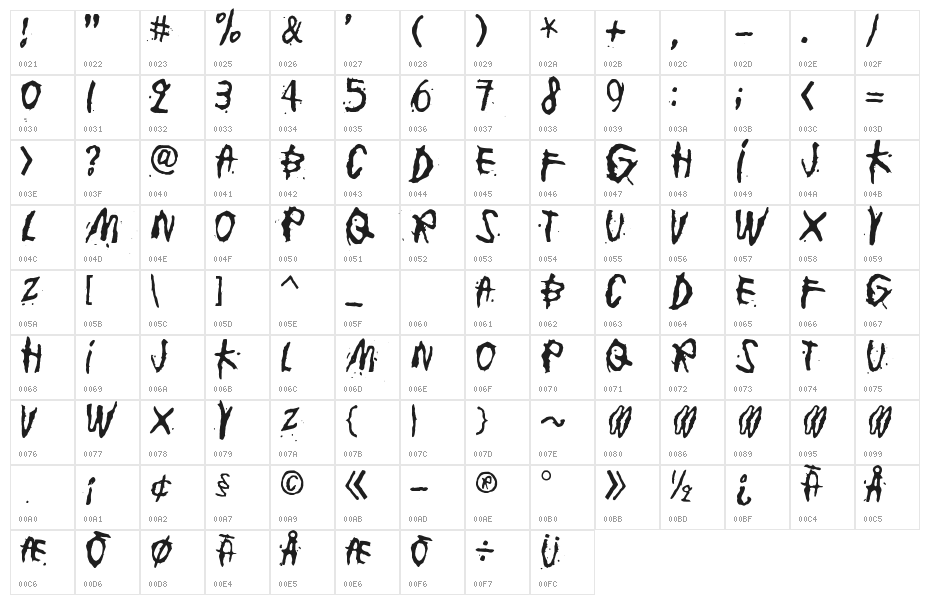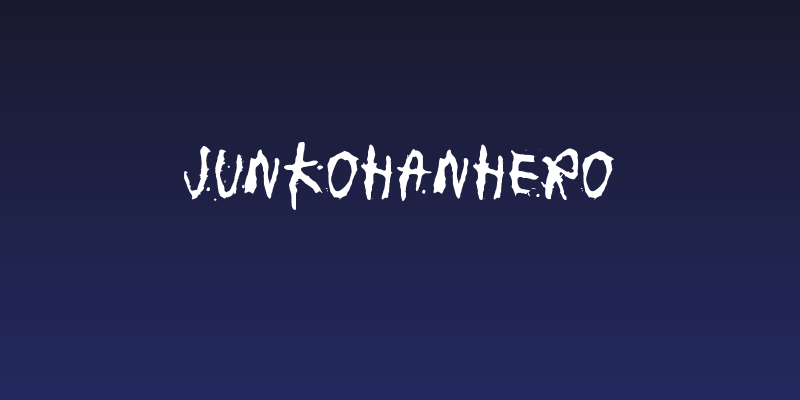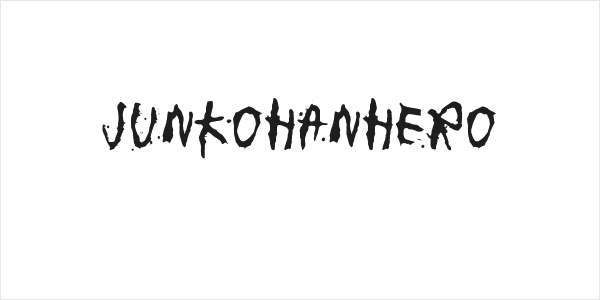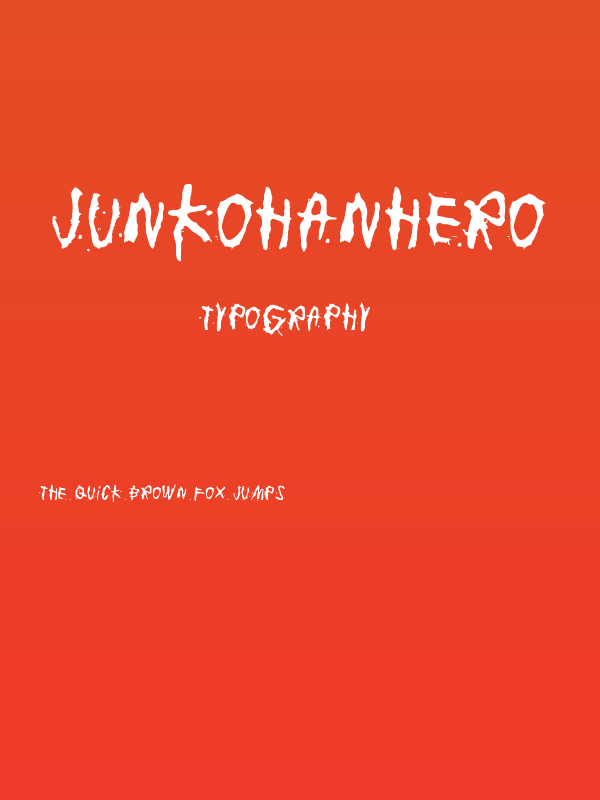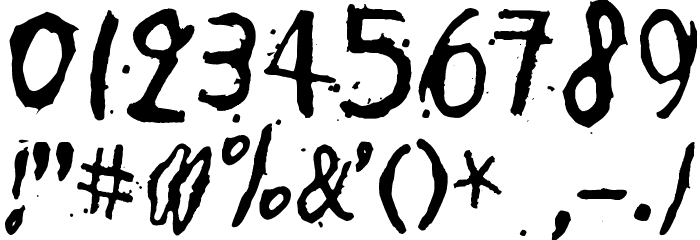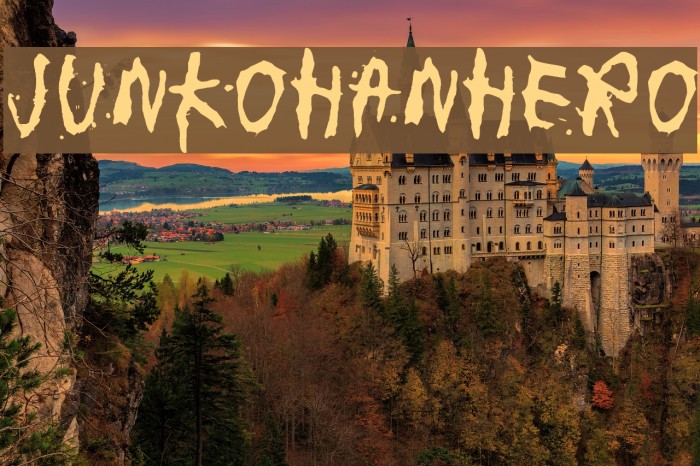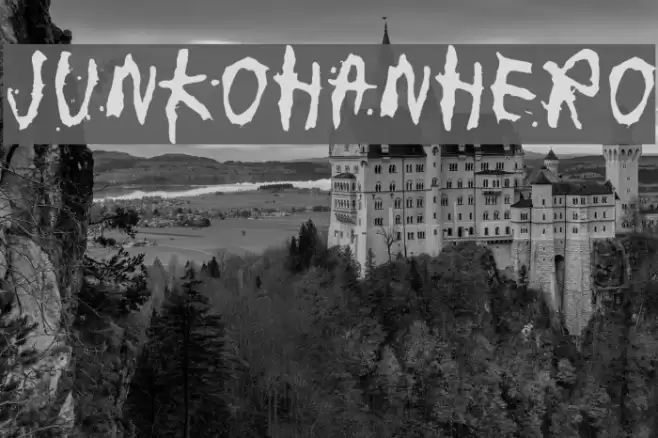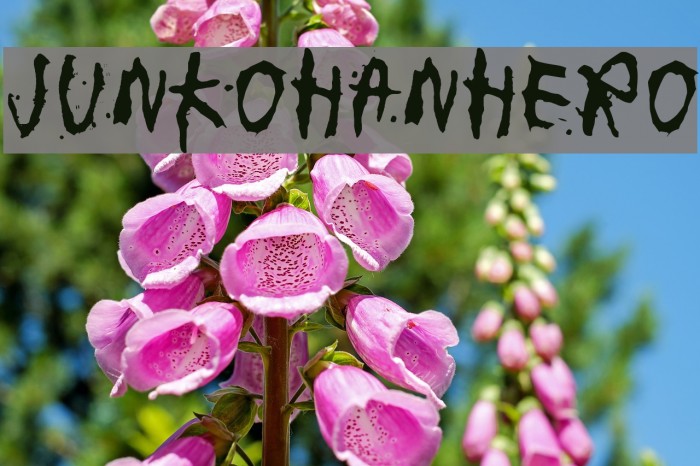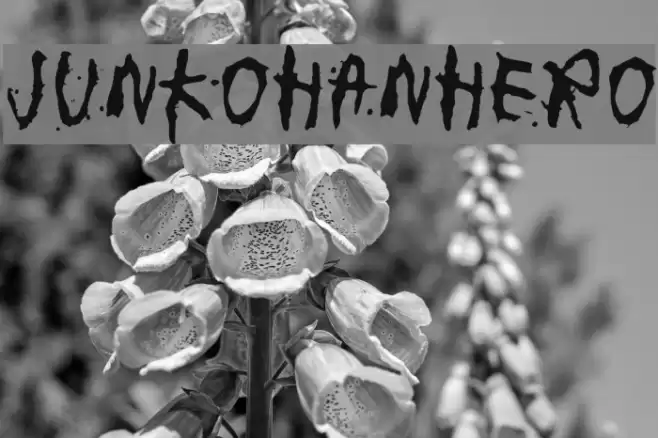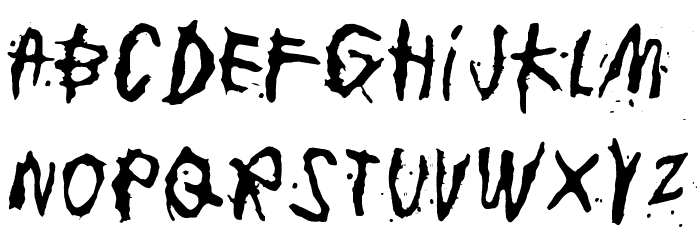
junkohanhero Font
| النمط العام | Artistic, Expressive, Raw |
| حالة الاستخدام | Headlines, Logos, Artistic projects |
| مشاريع مقترحة | Ideal for posters, album covers, creative branding, and artistic projects. |